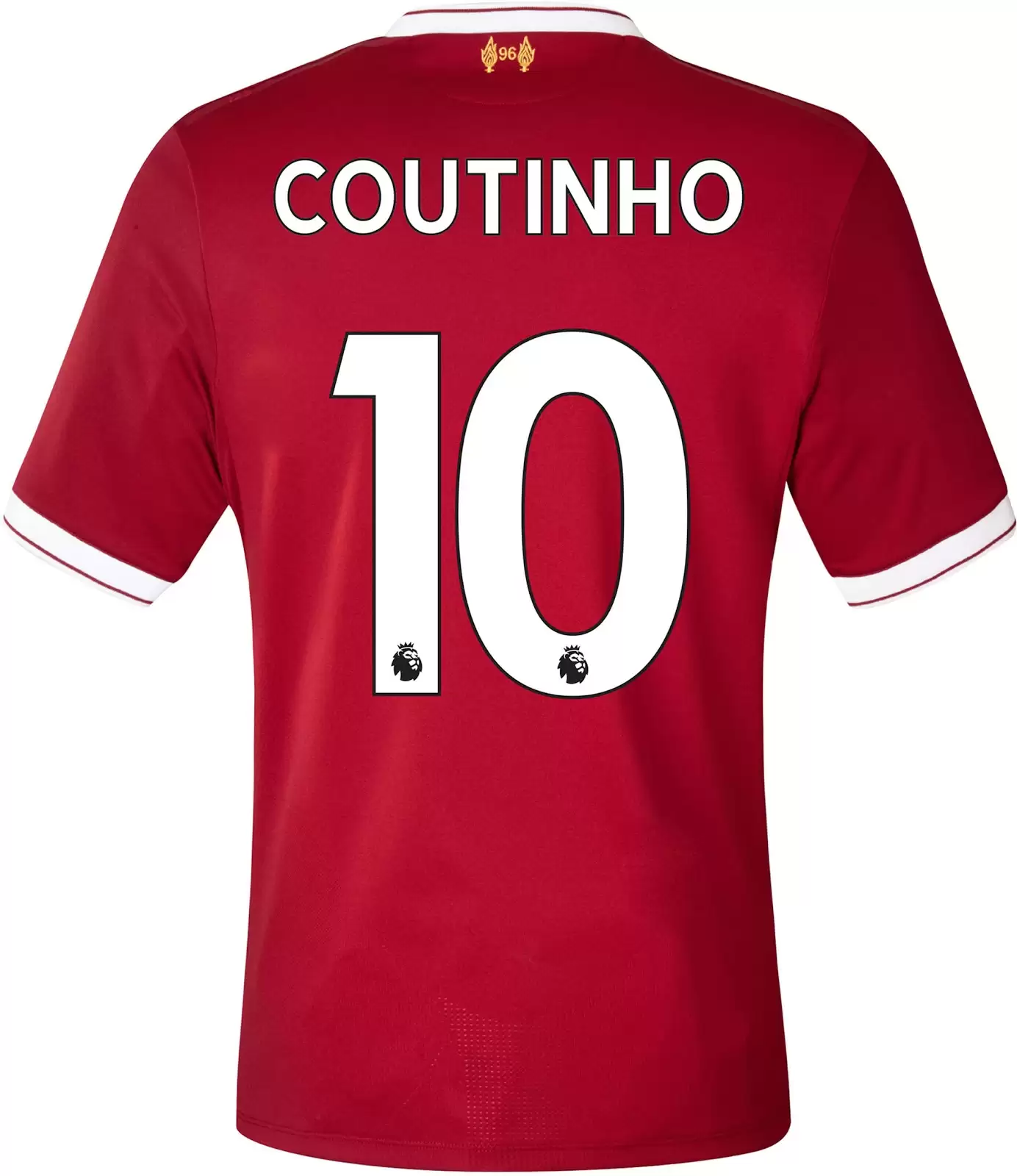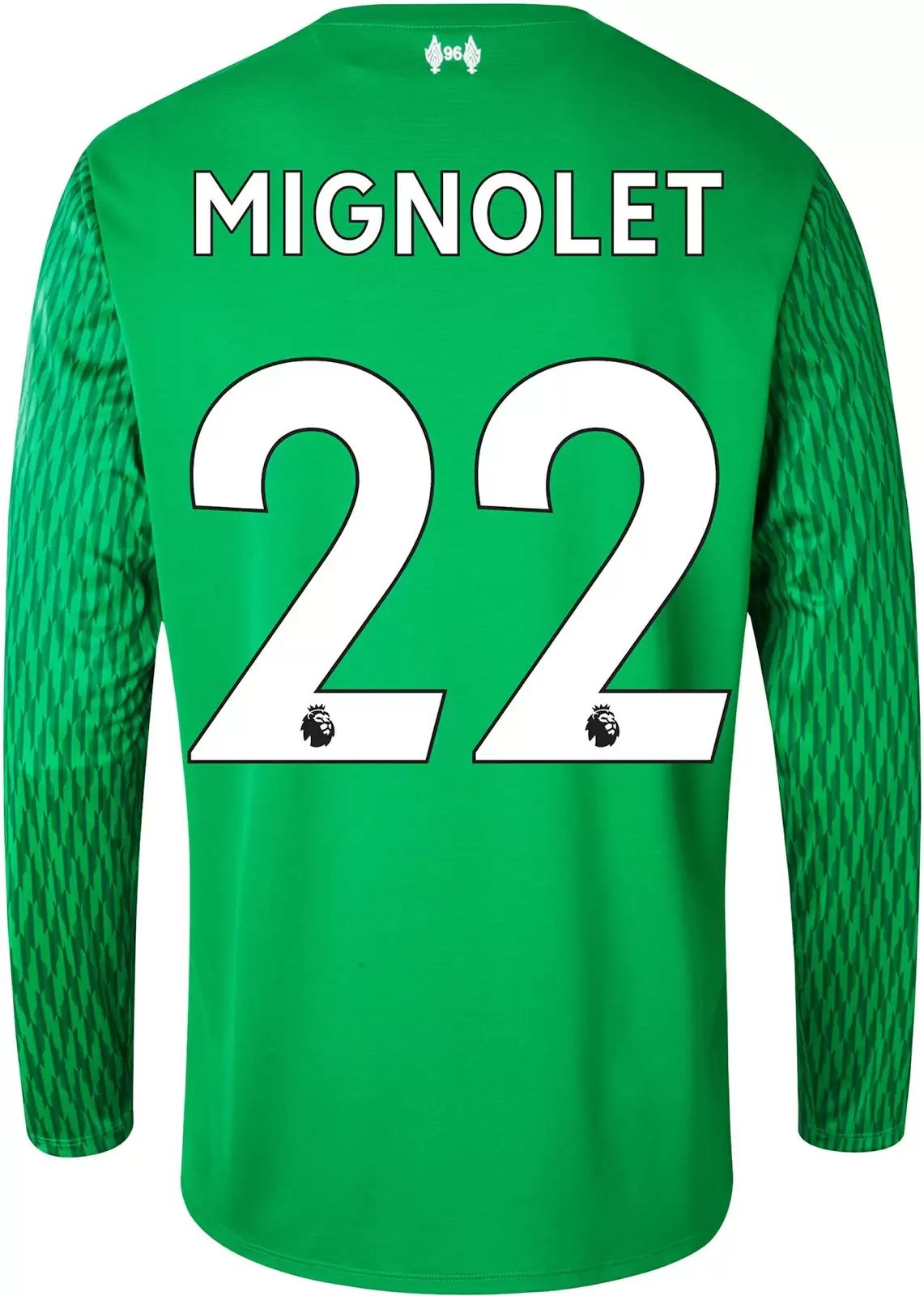
A pocas semanas de finalizar la temporada actual en la Premier League inglesa, el organismo encargado de diseñar la imagen del torneo, reveló el nuevo modelo de sus dorsales para el 2017/18.
Mediante un innovadora y elegante colección, el nuevo uniforme del Liverpool FC prestó sus dorsales para graficar cómo quedarían los nombre y números tanto en jugadores de campo como en su arquero.
Como es sabido, el logo distintivo del certamen estará impreso dentro de cada número, al igual que una de las mangas, mientras que la otra podrá contar con publicidad.
Mediante un innovadora y elegante colección, el nuevo uniforme del Liverpool FC prestó sus dorsales para graficar cómo quedarían los nombre y números tanto en jugadores de campo como en su arquero.
Como es sabido, el logo distintivo del certamen estará impreso dentro de cada número, al igual que una de las mangas, mientras que la otra podrá contar con publicidad.